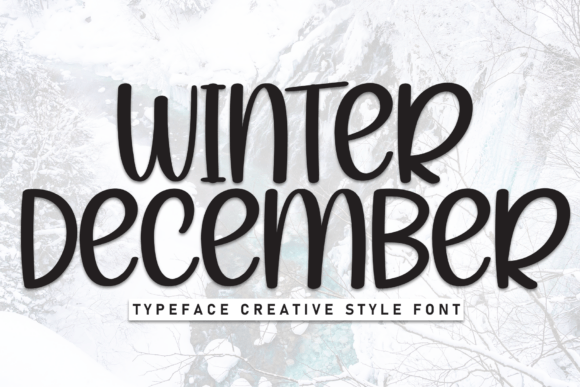
Winter December Font
Winter December Fontのような高品質の素材をお探しの場合、このプレミアムパッケージはクリエイティブなプロジェクトに素晴らしい選択です。
POD(オンデマンド印刷)製品、結婚式の招待状、またはソーシャルメディアのグラフィックを作成している場合でも、Winter December Fontは理想的です。